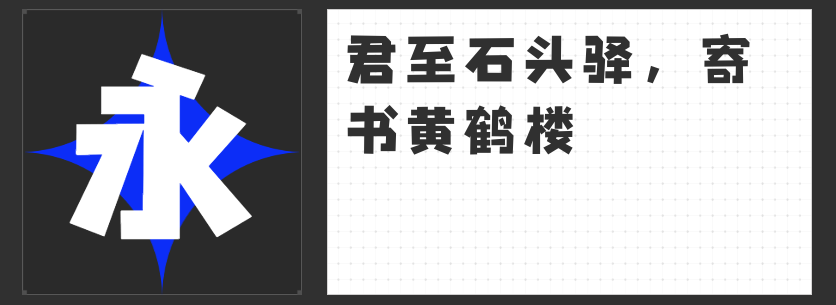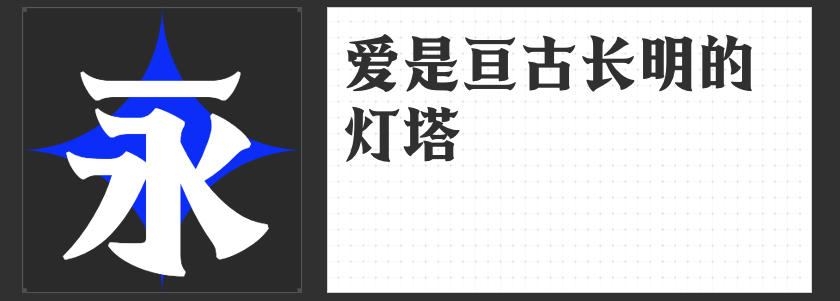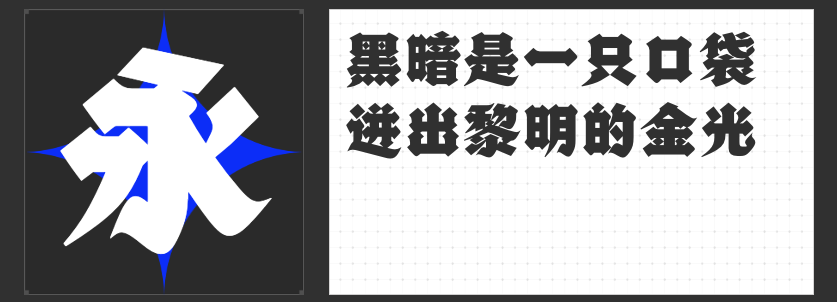
海报设计创意字体推荐:四款风格化字库解锁视觉张力
在海报设计的语境中,字体不仅是信息载体,更是传递情绪、塑造氛围的核心元素。一款契合主题的创意字体,能瞬间将观众拉入预设的视觉场域。本文精选四款风格鲜明的字库字体,从哥特式暗黑美学到国潮复古韵味,从仙侠古风到可爱折纸趣味,为设计师提供多样化的表达工具。
一、高手字斋哥特体Pro
以中世纪哥特式建筑为灵感,高手字斋哥特体Pro通过尖锐的笔画收尾、高对比度的粗细对比,构建出阴森而庄重的氛围感。其竖画如教堂尖塔般直指天际,横画则以锯齿状装饰强化金属质感,适合恐怖、奇幻、摇滚等主题海报的标题设计。字体在保留可读性的同时,通过非常规的笔画倾斜角度(如斜切式撇捺)打破平衡,为画面注入动态张力,尤其适合需要营造压迫感或神秘感的视觉叙事。
二、高手兵克侠客体
高手兵克侠客体将传统建筑美学融入字体设计,横画起笔与收笔处的上扬弧度模拟古建筑飞檐,竖画则以粗细渐变呼应斗拱结构,形成独特的“建筑式笔画”。其重心略高,字形修长,既保留了宋体的文人气质,又通过夸张的装饰性笔画(如钩画的延长与卷曲)强化复古感。这款字体尤其适合文化类、节日类海报,能以字形本身传递历史厚重感,无需额外装饰即可构建国潮视觉语言。
三、造字侠灵霄简繁 传神
取名自《西游记》灵霄宝殿的造字侠灵霄简繁 传神,以硬笔手写为基底,通过硬挺的笔画与均匀的布白,塑造出仙侠题材中常见的“剑气凌厉”感。其横画如刀削斧凿,竖画似长枪直刺,转折处干脆利落,毫无拖沓。字体结构借鉴书法中的“中宫收紧”原则,重心下沉而字形舒展,既适合作为网游、武侠剧海报的主标题,也能通过调整字号大小,构建主次分明的视觉层级。
四、创客贴石头体
创客贴石头体以“纸张折叠”为概念,将笔画转角处设计为90度直角折叠效果,模拟折纸的立体感与趣味性。其字形方正,但通过笔画粗细的微妙变化(如横细竖粗)打破呆板,搭配圆润的收笔处理,在可爱中透出一丝童趣。这款字体适合儿童产品、文创品牌或轻松向活动的海报设计,能以字形本身的趣味性弱化商业感,拉近与观众的情感距离。
创意字体的价值,在于其能以字形语言直接传递设计意图。这四款字体均通过独特的笔画处理与结构逻辑,为海报设计提供了丰富的风格化选择。设计师可根据主题需求,选择与画面情绪高度契合的字体,让文字从“配角”升级为“视觉主角”。